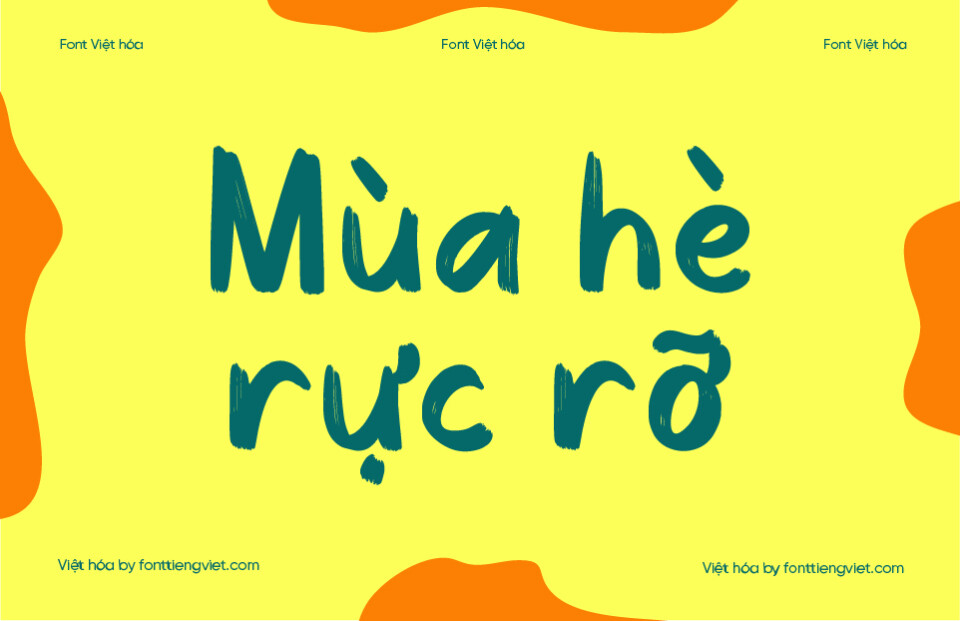
Khám phá sự Tươi Mới Cùng Font Việt hóa 1FTV VIP Cheerful Summer – Brush
Trong thế giới thiết kế đồ họa đầy màu sắc, việc lựa chọn một Font Chữ phù hợp có thể quyết định đến sự thành công của toàn bộ dự án. Đặc biệt, khi các dự án cần truyền tải năng lượng tích cực, sự vui vẻ và tinh thần mùa hè sảng khoái, thì Font Việt hóa 1FTV VIP Cheerful Summer – Brush chính là lựa chọn không thể bỏ qua. Đây không chỉ là một phông chữ cọ (brush font) thông thường mà còn là một tác phẩm đã được Việt hóa kỹ lưỡng, đảm bảo hiển thị hoàn hảo mọi dấu tiếng Việt từ các bài luận văn, poster sự kiện cho đến những thông báo quan trọng của trường học và các buổi lễ tốt nghiệp. Hãy cùng đi sâu vào những đặc điểm nổi bật khiến font chữ này trở thành “must-have” trong bộ sưu tập typography của bạn.
Điểm Nhấn Nổi Bật Của Font Việt hóa 1FTV VIP Cheerful Summer – Brush
Phong cách cọ vẽ (Brush Style) luôn mang lại cảm giác chân thực, nghệ thuật và cá nhân hóa cao. Với 1FTV VIP Cheerful Summer, nhà thiết kế đã tạo ra một phông chữ có độ chảy tự nhiên, mô phỏng nét viết tay phóng khoáng của cọ vẽ, rất phù hợp cho các thiết kế mang tính chất sáng tạo và năng động. Khác biệt lớn nhất của phiên bản Việt hóa này là sự tương thích tuyệt đối với tiếng Việt, bao gồm các ký tự đặc biệt như ơ, ư, ă, â, ê, và các dấu thanh. Điều này loại bỏ hoàn toàn lỗi hiển thị hay mất dấu thường gặp ở các font nước ngoài chưa được xử lý.
Sự “Cheerful Summer” thể hiện rõ qua các đường nét dày dặn, bo tròn nhẹ nhàng, tạo cảm giác thân thiện, dễ đọc dù là ở kích thước lớn trên banner hay kích thước nhỏ trong thiệp mời. Độ tương phản cao và cấu trúc rõ ràng giúp font này dễ dàng nổi bật trên mọi nền, từ nền ảnh chụp bãi biển đến nền màu đơn sắc. Đây là giải pháp hoàn hảo cho các dự án yêu cầu sự trẻ trung, từ thiết kế áo lớp, kỷ yếu tốt nghiệp cho đến các chiến dịch marketing hướng tới đối tượng học sinh, sinh viên.
Ứng Dụng Đa Dạng Của Phông Chữ Cọ Trong Thiết Kế Giáo Dục và Sáng Tạo
Đối với các trường học và học sinh, sinh viên, nhu cầu về một phông chữ vừa chuyên nghiệp vừa mang tính nghệ thuật là rất lớn. Font 1FTV VIP Cheerful Summer – Brush đáp ứng được cả hai tiêu chí này.
- Thiết Kế Kỷ Yếu Tốt Nghiệp: Phông chữ này mang lại sự độc đáo cho tiêu đề các chương, tên lớp học, hoặc các câu trích dẫn đáng nhớ trong cuốn kỷ yếu, làm tăng giá trị thẩm mỹ và sự cá nhân hóa.
- Poster Sự Kiện Trường Học: Từ các thông báo về hoạt động hè, cuộc thi tài năng, đến các buổi ôn tập chuẩn bị cho kỳ thi tốt nghiệp THPT quốc gia, phông chữ này giúp poster trở nên bắt mắt và thu hút sự chú ý của học sinh.
- Branding Cá Nhân và Dự Án Học Tập: Sinh viên theo học các ngành thiết kế, truyền thông có thể sử dụng font này để xây dựng thương hiệu cá nhân hoặc làm nổi bật các dự án sáng tạo của mình, thể hiện tinh thần không ngừng học hỏi và khám phá.
- Thiệp Mời và Thông Báo: Tạo ra những thiệp mời dự lễ tốt nghiệp hoặc thư cảm ơn có phong cách riêng biệt, ấm áp và gần gũi.
Việc sử dụng các font chữ đẹp, được Việt hóa hoàn chỉnh như Font Việt hóa 1FTV VIP Cheerful Summer – Brush giúp đảm bảo tính nhất quán và chất lượng cao cho các tài liệu in ấn và kỹ thuật số, đặc biệt quan trọng trong các tài liệu chính thức liên quan đến giáo dục và thi cử.
Bí Quyết Tối Ưu Hóa Thiết Kế Với Font Chữ Cheerful Summer
Để tận dụng tối đa vẻ đẹp của phông chữ cọ vẽ này, hãy lưu ý một số mẹo nhỏ. Do tính chất “brush” mạnh mẽ, font này hoạt động tốt nhất khi được sử dụng cho tiêu đề hoặc các đoạn văn ngắn, nhấn mạnh. Hạn chế sử dụng nó cho các khối văn bản dài để tránh gây mỏi mắt. Luôn kết hợp nó với một font chữ sans-serif hoặc serif cơ bản, dễ đọc cho phần nội dung chi tiết. Ví dụ, dùng 1FTV VIP Cheerful Summer cho tên sự kiện, và dùng Roboto hoặc Times New Roman cho mô tả sự kiện. Sự tương phản này sẽ tạo ra một thiết kế cân bằng và chuyên nghiệp. Khi chuẩn bị các tài liệu liên quan đến kỳ thi hay các dự án học thuật, việc kiểm tra kỹ lưỡng bản Việt hóa là bước không thể thiếu, và may mắn thay, font này đã được tối ưu hóa hoàn hảo.
Tóm lại, nếu bạn đang tìm kiếm một Font Chữ mang lại sự sống động, năng lượng tích cực và chất lượng Việt hóa tuyệt vời cho các dự án thiết kế mùa hè, hay các ấn phẩm liên quan đến học đường và tốt nghiệp, thì Font Việt hóa 1FTV VIP Cheerful Summer – Brush chính là lựa chọn hàng đầu. Với phong cách cọ vẽ hiện đại, dễ dàng ứng dụng trong nhiều bối cảnh từ thiệp mời, poster cho đến các tài liệu học tập quan trọng, font này chắc chắn sẽ nâng tầm thiết kế của bạn. Đừng chần chừ, hãy bổ sung ngay phông chữ tươi mới này vào thư viện của bạn để thỏa sức sáng tạo không giới hạn.